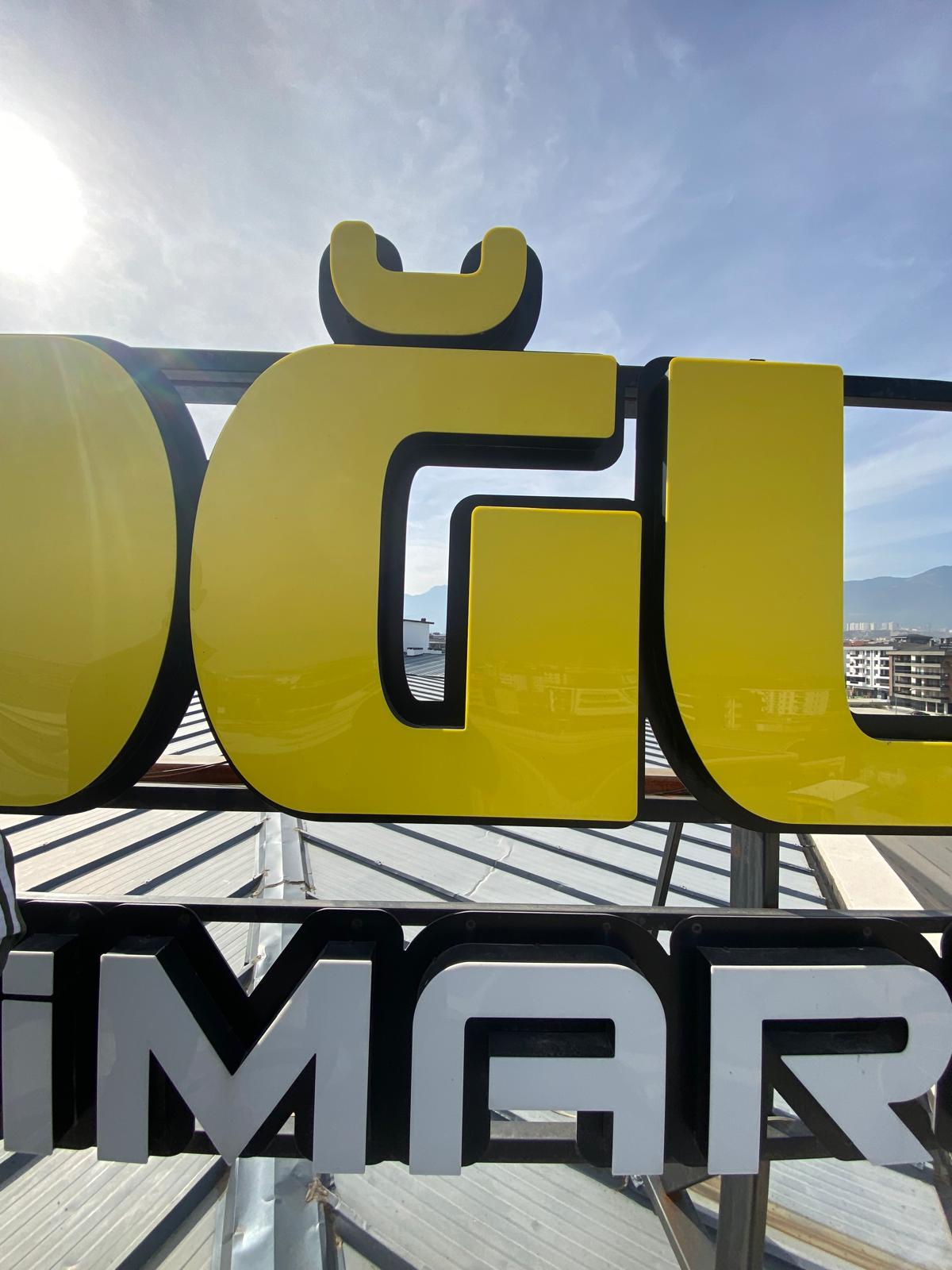
Tabeladaki Font İsteği
- 03-11-2025, 17:51:54Selamlar bu tabeladaki sarı ve beyaz kutu harfde kullanılan font bilen varmıdır teşekkürler.
- 03-11-2025, 20:16:27Görseldeki tabela gölgelendirilmiş aynısını bulmazsın düz hali lazımserdarcolak adlı üyeden alıntı: mesajı görüntüle
- 03-11-2025, 20:23:33Eurostile Bold Extended
Microgramma Bold Extended- Eurostile Bold Extended
- Microgramma Bold Extended
- Bank Gothic Medium (biraz daha keskin köşeli)
- Ethnocentric Bold (daha fütüristik bir versiyonu)
Gene olmadı tabeladaki firmanın kurumsal görsellerinden çıkartırız